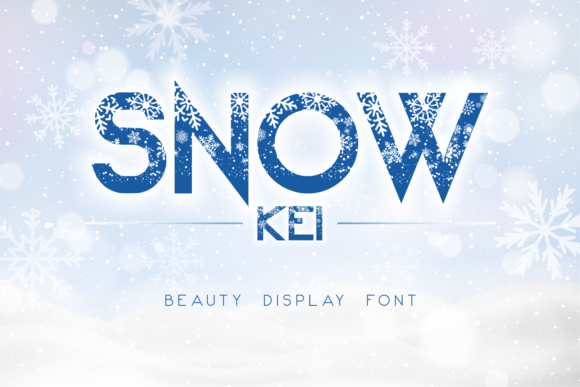
Esta é uma fonte sans-serif para uso em exibição que se chama Snow Kei Font. Inspirada nas festividades invernais, esta elegante e acolhedora fonte sem serif traz a atmosfera do inverno com leveza e conforto. O ornamento de neve presente no topo da fonte intensifica ainda mais o clima quente e autêntico do inverno. Introduzida especialmente para projetos que incluem logos, identidades de marca, gráficos blogueiros, citações estilizadas, decoração nupcial, impressões artísticas, design collateral, embalagens, mídias sociais e muito mais. Se você está procurando por uma fonte perfeita para suas criações que transmitem o encanto da primavera de inverno, a Snow Kei Font pode ser exatamente aquilo que você precisa. Suas detalhes divertidos e inusitados remetem diretamente aos dias entrelaçados de neve e sol do inverno. Sem dúvida, esta fonte oferece uma excelente maneira de adicionar personalidade a qualquer projeto visual, tornando-o ainda mais envolvente e autêntico, proporcionando um toque único que se encaixa perfeitamente em seu design.